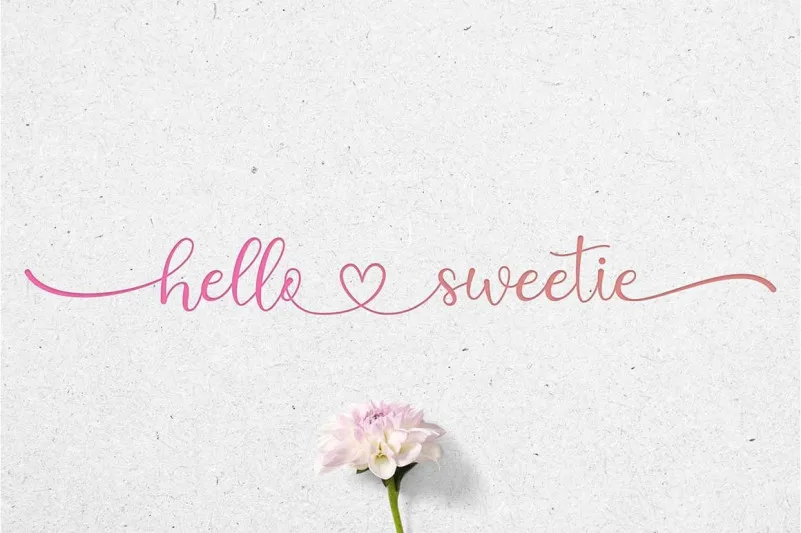
Hello Sweetie Font – Download Grátis
Esta fonte ‘Hello Sweetie Font’ é uma perfeita escolha para quem busca elegância e versatilidade no seu trabalho. Desenhada sob a forma de um belo círculo do script calligrafia, ela parece flutuar pela página com sua beleza natural. Esta fonte é única em termos de formas redondas e bem definidas, tornando-a um verdadeiro trabalho de arte para qualquer projeto que você estiver criando. Com uma aparência atraente e extremamente versátil, ‘Hello Sweetie Font’ se torna sua amiga inseparável. Suaviza designs simples e transforma layouts tradicionais em algo novo e incrivelmente sofisticado. É perfeita para aqueles que buscam adicionar um toque de elegância a suas criações sem deixar de lado sua personalidade única. A fonte ‘Hello Sweetie Font’ é ideal tanto para designers profissionais quanto para quem está apenas começando, oferecendo flexibilidade em termos de design. É perfeito para rótulos e títulos em seu site, letras nos produtos, ou qualquer coisa que você possa imaginar decorar com a delicadeza deste design elegante.